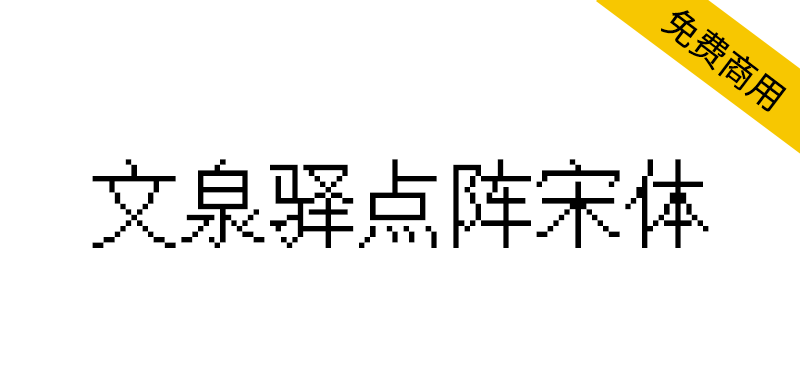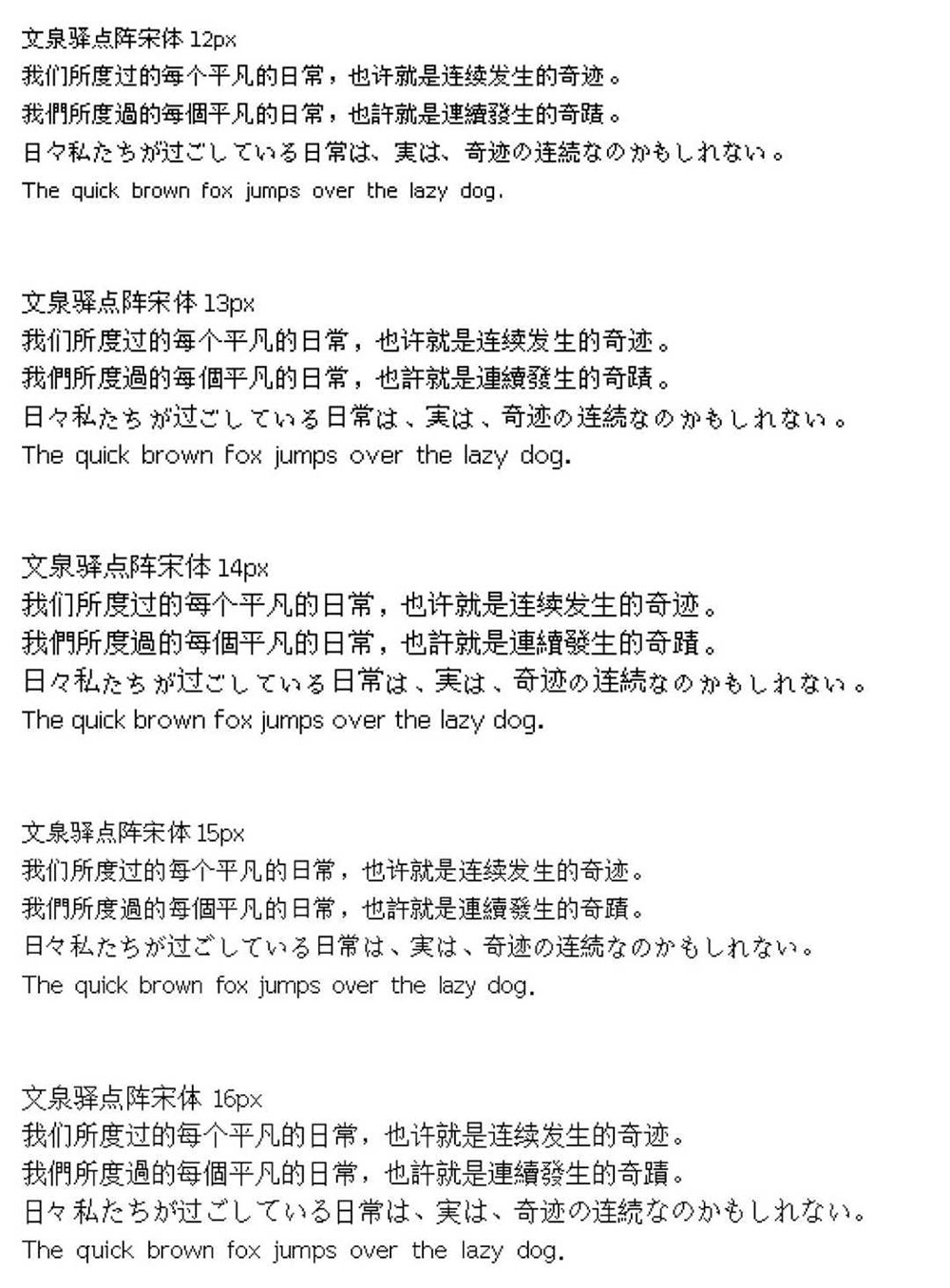
文泉驿点阵宋体是一个"自由中文字体"。该字体包含了所有常用简体中文、繁体中文,日文及韩文所需要的汉字(最新版本包含超过27842个汉字,完整覆盖GB2312/Big5/GBK/GB18030标准字符集)。该字体同时还包含了英文、日文、韩文和其他多种语言符号。该点阵字体包含五个屏幕常用字号(9pt-12pt),逾21万汉字点阵,这些点阵都经过参与者和组织者的精心设计和调整,手工优化后的汉字点阵显示清晰锐利,特别易于屏幕阅读使用。